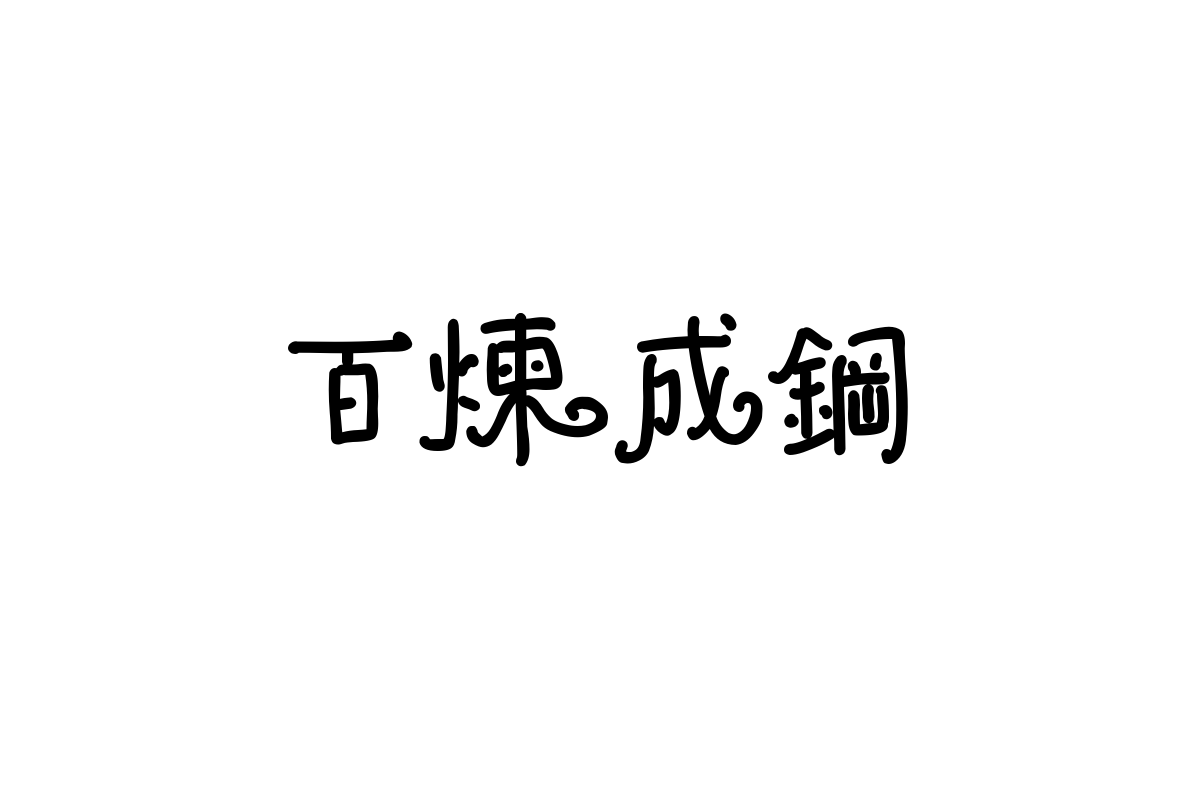
造字工房丁丁体是一款由造字工房公司设计的字体。这款字体的特点是字形独特,线条流畅,给人一种简洁、明快的感觉。它的笔画粗细适中,既适合用于标题、正文等需要突出重点的场合,也适合用于广告、包装等需要吸引眼球的场合。此外,造字工房丁丁体还具有很好的可读性,适用于多种场景,如网页、报纸、杂志等。总的来说,造字工房丁丁体是一款非常实用的字体,值得一试。